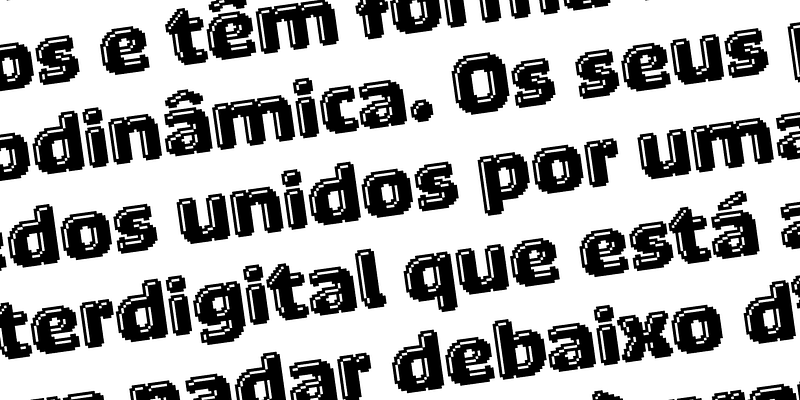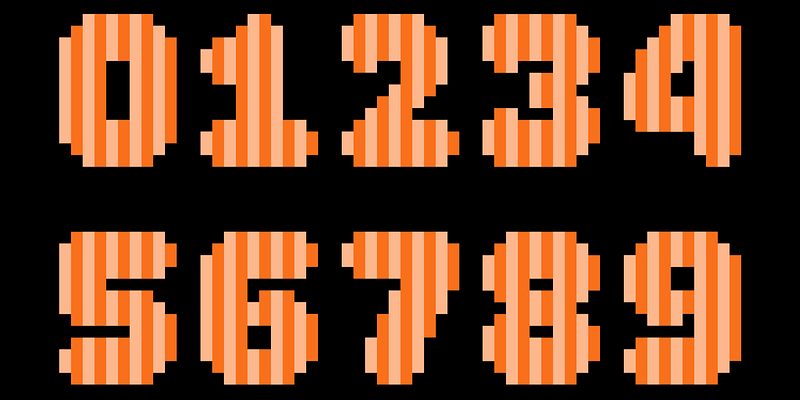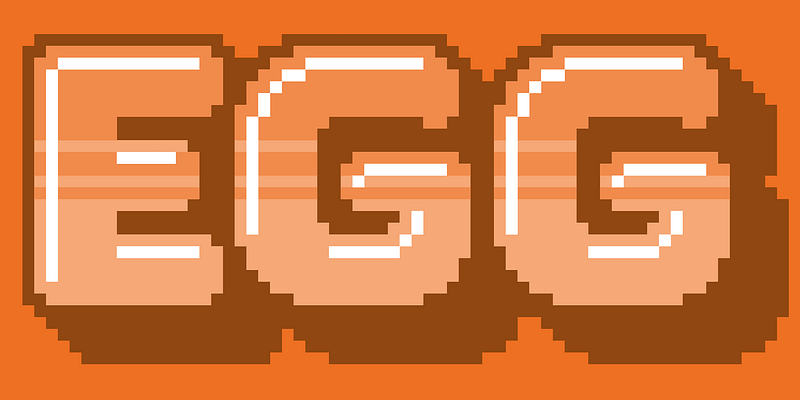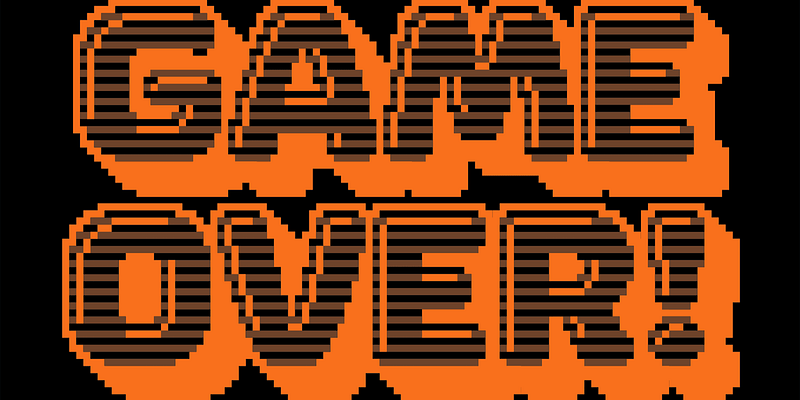
Puffin Arcade est une famille ludique de 12 polices bitmap basées sur la graisse la plus élevée de Puffin Display Soft. Tous les styles individuels, à l’exception de Stencil, peuvent être superposés les uns sur les autres pour un effet supplémentaire. Ils ne demandent qu’à être utilisés dans des animations multicolores, clignotantes ou en mouvement. Si nécessaire, vous pouvez reprendre le contrôle des choses et combiner les polices avec les styles plus sages Puffin et Puffin Display.